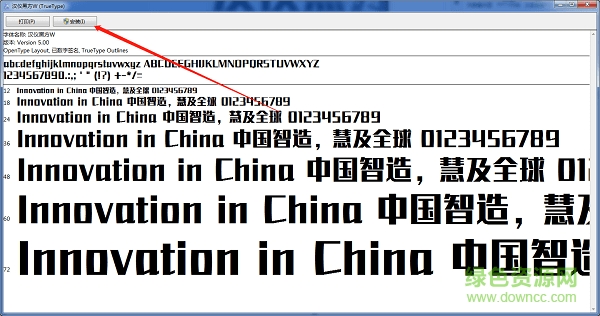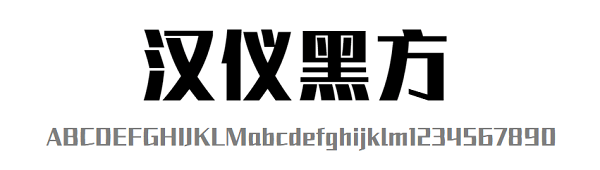
漢儀黑方w字體是一款看起來非常精神醒目的黑體字體,整個字體棱角分明,非常具有畫面感,能夠給給人一種非常醒目的感覺,需要的用戶快來綠色資源網(wǎng)下載吧!
漢儀黑方W字體是由漢儀字庫打造的一款黑粗字體,給人的第一眼就是看上去非常方方正正的,筆畫也是非常的粗,給人的印象非常深刻,如果有感興趣的可以來免費下載收藏!
-字體非常方正,筆畫也很粗,很有黑體的特色,而且重心較高,看起來也比較高挑,
-向下書寫的筆畫略微增加了一些弧度,讓字體看起來不是那么死板,也增加了一些個性,
-可用于標(biāo)題、海報、封面、包裝等多種應(yīng)用場景。